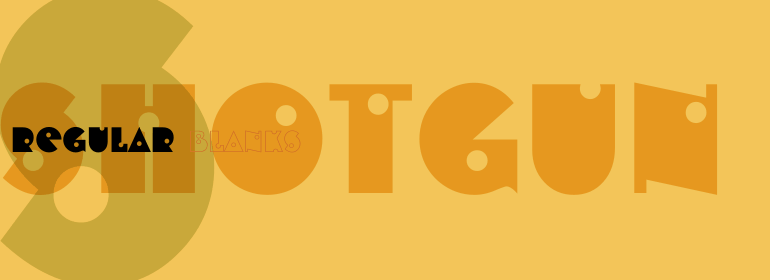
Shotgun
Shotgun,这款字体结构工整、笔画清晰,兼顾美观与易读性,适用于标题、正文、海报、包装、LOGO 等多种场景。字形优雅稳定,风格百搭耐看,适配日常排版与创意设计,让文字呈现更舒适、更具质感。Shotgun一笔一画,皆是细节,以均衡的比例、流畅的线条打造舒适视觉体验,字形端正大气,风格简约现代。无论是商业设计、品牌宣传还是日常排版,都能轻松驾驭,让文字更有格调与力量。Shotgun字体下载。
字体品牌: Bitstream(Monotype) 设计师:Looney,J. 字体分类:衬线体 字体属性:外文 字符集:Unicode 发布时间: 2018